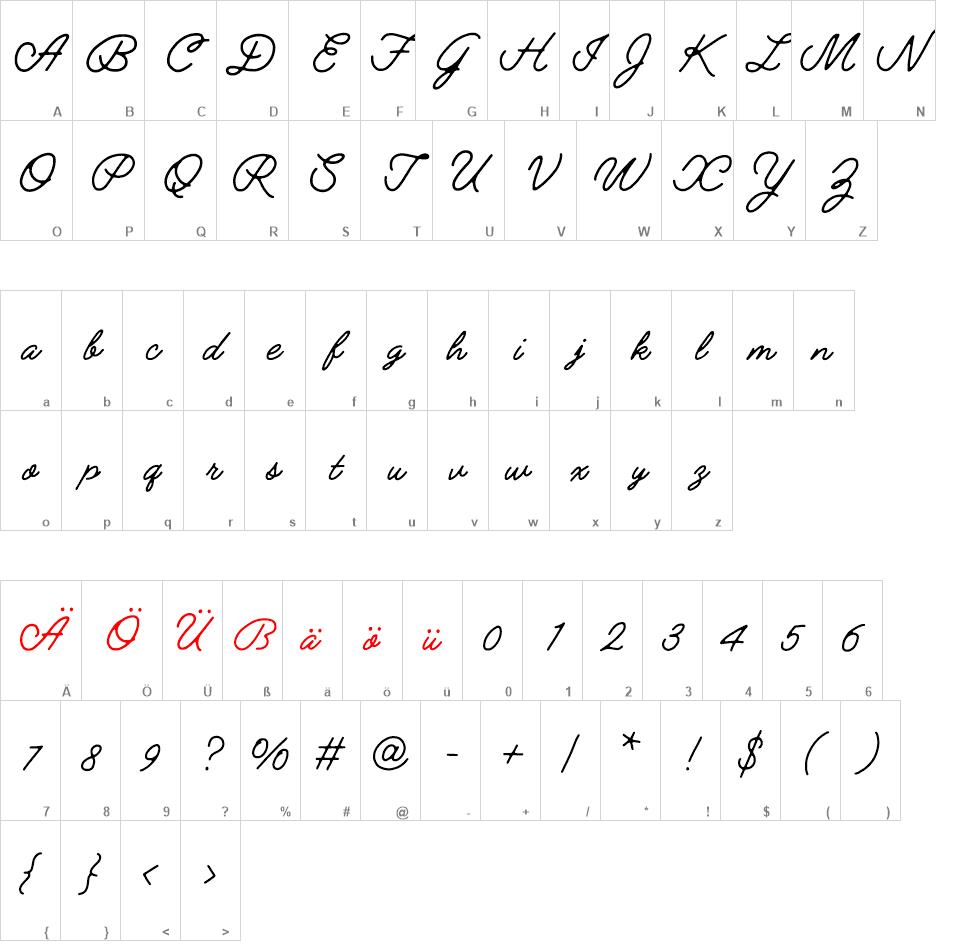
Jimmy Script
Ich freue mich, Ihnen meine Jimmy Script-Schriftart mitzuteilen. Sein Design wurde vom modernen Vintage-Trend inspiriert, der die Designbranche erobert.